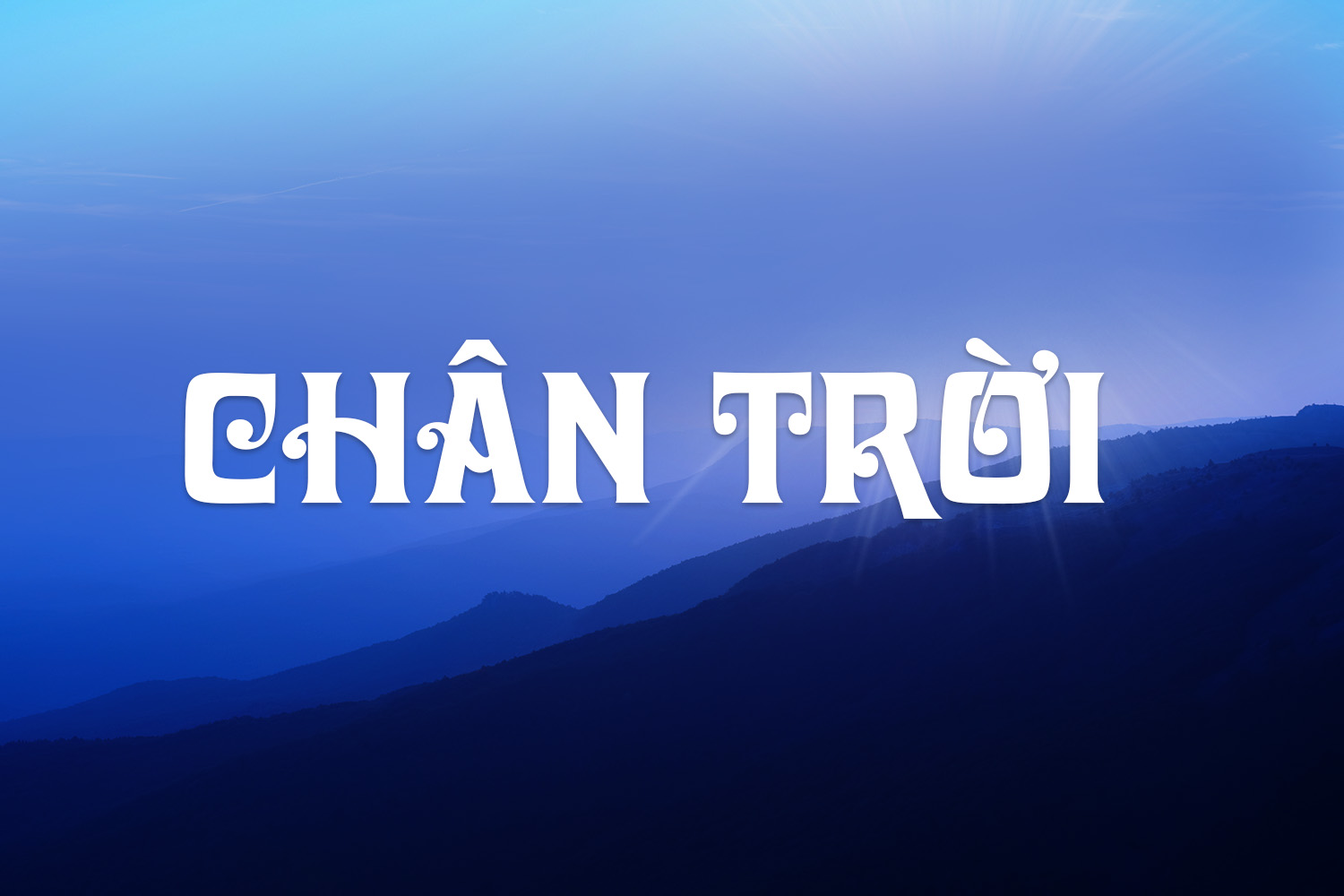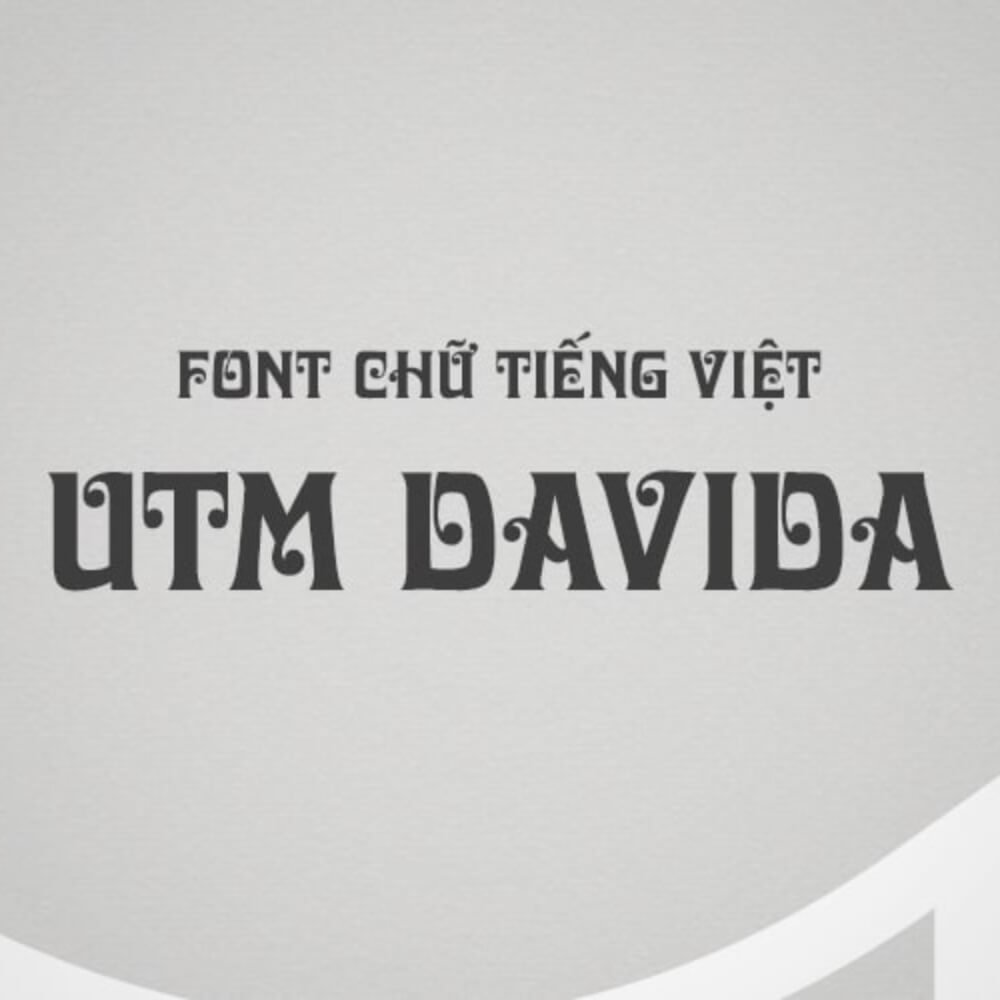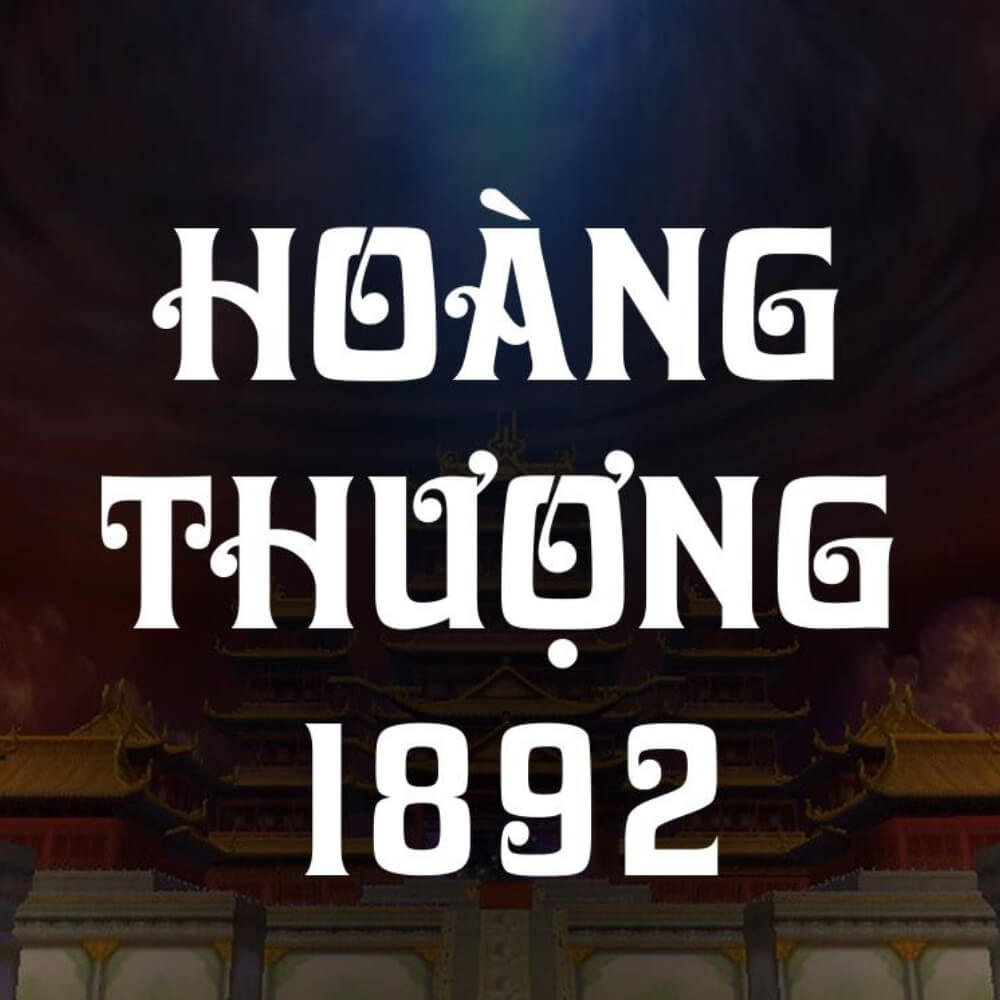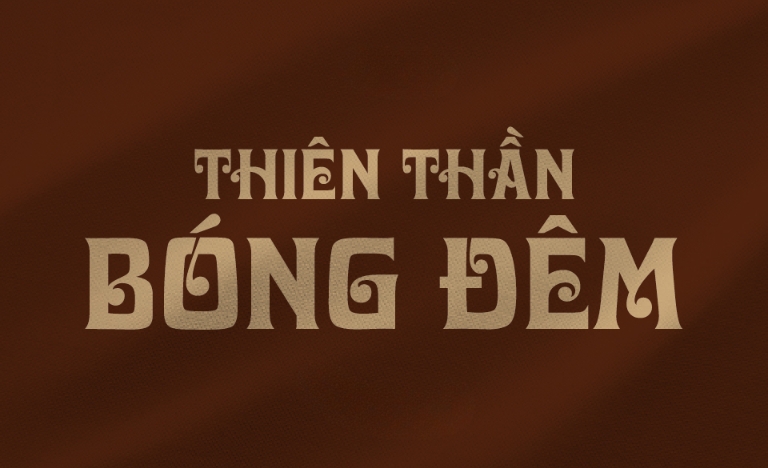
UTM Davida mang phong cách trang trí cổ điển với những đường nét dày dặn, các chi tiết uốn cong độc đáo gợi nhắc đến vẻ đẹp của các thiết kế thời kỳ Victoria. Đây là bộ font chữ sở hữu cá tính mạnh, thường được ưu tiên để tạo ra sự khác biệt và sang trọng cho các tiêu đề hoặc bảng hiệu. Thư viện tài nguyên của BCD House chia sẻ bộ font Việt hóa UTM Davida nhằm hỗ trợ cộng đồng kiến trúc và thiết kế có thêm phương án trình bày ý tưởng một cách lôi cuốn và chuyên nghiệp.
Khám phá nét độc đáo của font Việt hóa UTM Davida
Nét đặc trưng của Davida nằm ở sự kết hợp giữa các cột chữ vững chãi và những đường bo góc cầu kỳ, mang lại cảm giác hoài cổ nhưng vẫn đầy quyền lực. Bản utm davida việt hóa đã được xử lý bảng mã Unicode chuẩn, giúp người dùng gõ tiếng Việt ổn định mà không gặp tình trạng sai ký tự hay lỗi dấu thanh. Điều này mang lại sự thuận tiện khi triển khai các hồ sơ thiết kế, giúp văn bản duy trì được tính thẩm mỹ đồng nhất từ bản vẽ kỹ thuật đến ấn phẩm truyền thông.
Bên cạnh yếu tố trang trí, font davida việt hóa còn có khả năng hiển thị khá ấn tượng trên nhiều chất liệu in ấn. Dù được sử dụng trên nền gỗ, kim loại hay hiển thị trên các nền tảng kỹ thuật số, các chi tiết đặc trưng của bộ chữ vẫn giữ được độ sắc sảo. Đây là lựa chọn phù hợp cho những dự án kiến trúc và nội thất hướng đến phong cách sang trọng, cổ điển hoặc cần tạo điểm nhấn thị giác mạnh mẽ.
| Phong cách thiết kế | Decorative / Classic / Serif |
| Lĩnh vực phù hợp | Tiêu đề, Bảng hiệu, Logo, Decor |
Tư vấn trình bày: Do utm davida font có cấu trúc dày và nhiều chi tiết trang trí, bạn nên đặt font này trên các nền màu đơn sắc hoặc có ít chi tiết gây nhiễu để tôn vinh được vẻ đẹp cổ điển của từng ký tự.
03 Ứng dụng font chữ UTM Việt hóa Davida vào đời sống
Với vẻ ngoài giàu tính nghệ thuật, bộ font chữ này mang lại giá trị thực tế cao khi được đưa vào thực tế trang trí và quảng bá công trình:
- Thiết kế bảng tên khu nghỉ dưỡng cao cấp: Những đường nét cổ điển của Davida rất ăn ý khi xuất hiện trên biển hiệu của các khu homestay container hoặc nhà lắp ghép mang phong cách châu Âu. Font chữ này giúp không gian toát lên vẻ chuyên nghiệp và tinh tế.
- Trang trí không gian nội thất Retro: Bạn có thể sử dụng font chữ utm việt hóa này để cắt chữ nổi laser làm điểm nhấn tại phòng khách, quầy lễ tân hoặc các quán cafe nghệ thuật, giúp khơi gợi cảm hứng hoài cổ cho khách hàng.
- Tiêu đề hồ sơ dự án kiến trúc: Sử dụng font Davida cho các trang bìa hồ sơ hoặc các đề mục lớn giúp báo cáo của bạn trở nên ấn tượng và thể hiện rõ gu thẩm mỹ cá nhân của người kiến tạo.
03 Lưu ý kỹ thuật khi trình bày văn bản với utm davida việt hóa
Để khai thác hiệu quả vẻ đẹp của dòng font trang trí đậm nét này mà không làm rối mắt người xem, người thiết kế nên lưu tâm một số điểm sau:
- Hạn chế dùng cho nội dung chi tiết: Tuyệt đối tránh sử dụng Davida cho các đoạn thuyết minh dài hay ghi chú thông số kỹ thuật nhỏ, vì cấu trúc chữ dày sẽ gây khó đọc và làm mất đi sự mạch lạc của thông tin.
- Kiểm soát khoảng cách giữa các chữ: Một số ký tự trang trí có thể trông sát nhau khi viết các từ dài. Bạn nên nới rộng khoảng cách ký tự (Tracking) một chút để tổng thể văn bản trông thoáng và chỉn chu hơn.
- Phối hợp cùng font tối giản: Hãy thử kết hợp Davida cho phần tiêu đề và một font chữ không chân (Sans-serif) đơn giản cho phần văn bản chi tiết để tạo sự cân bằng về thị giác.